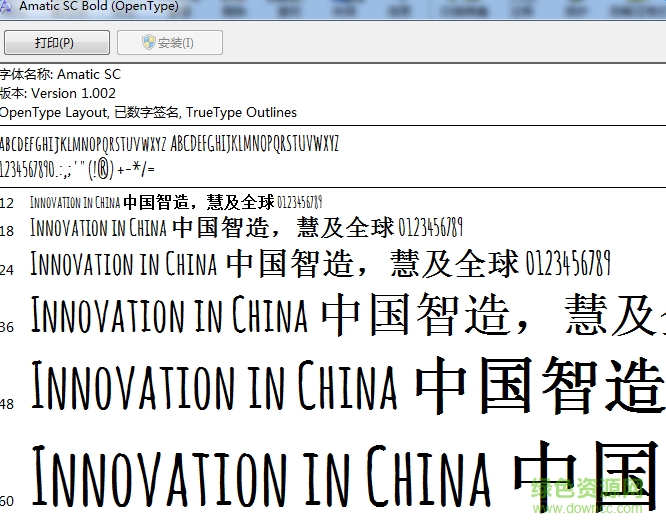
amatic bold字體是英文字體庫中的個性字體,該字體可以適用于產(chǎn)品包裝、廣告宣傳、出版印刷、商標用字、商業(yè)網(wǎng)站、影視影像視頻、書籍出版印刷等,有需要的朋友可以免費下載收藏。
amatic bold字體一款極具個性的英文字體,字體筆畫非常尖銳,讓人一眼就能看明白。有需要的朋友可以來綠色資源網(wǎng)下載使用!